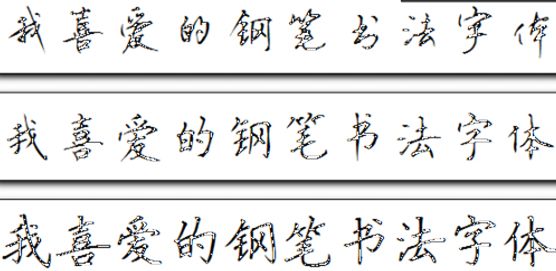
軟件介紹 軟件標簽: 字體 鋼筆字體 鋼筆硬筆書法字體有很多,小編在這里精選出三款鋼筆硬筆字體,大氣切底蘊足,自認為是目前為止較好的鋼筆書法字體:博洋楷體7000.TTF博洋行書7000.TTF方正硬筆楷書簡體.TTF 字體存放位置:c盤-windows -fonts 軟件截圖 上一張下一張(1 / 1) 安裝詳細截圖 猜你喜歡 鋼筆字體 書法字體 鋼筆字體 鋼筆字體是設計領域經常用到的字體,鋼筆字體具有鮮明的個人特征,風格多樣,深受廣告設計、平面設計師的喜愛,除了一些手寫鋼筆字體,還有正楷、行書類的鋼筆字字體,為設計師們提供了豐富的字體形式,綠色資源網也有很多鋼筆字體下載和鋼筆字體包,需要的可以看一看 查看更多>> 鋼筆書法軟件手機版 93.56M/中文/10.0/v2.1.5 安卓版下載 鋼筆之家 4.83M/中文/10.0/v1.0.2 安卓版下載 鋼筆手寫字體免費 11.71M/中文/1.2/下載 鋼筆書法入門基知識 31.79M/中文/5.0/v6.3.1 安卓版下載 浮生體 1.92M/中文/5.0/下載 伯樂鋼筆行書字體 3.53M/中文/6.6/下載 書法字體 書法字體有哪些?主要包括了硬筆書法字體、英文書法字體和毛筆書法字體三大類,綠色資源網提供了多款好看的常用各種書法字體文件打包下載,如:李旭科書法字體、啟功書法字體等,趕快下載體驗吧! 查看更多>> 蔡云漢隸書書法字體ttf 2.61M/中文/10.0/下載 黃庭堅字體 2.39M/中文/6.6/下載 李旭科書法v1.4-中 3.59M/中文/7.7/下載 金梅書法豆豆 2.03M/中文/10.0/下載 金梅新海報書法 2.24M/中文/10.0/下載 劉夢吟書法行楷字體 3.66M/中文/10.0/下載 其他版本下載 標題 大小 更新日期 下載 下載地址 電腦版 鋼筆硬筆書法字體 精選3款 點擊報錯 軟件無法下載或下載后無法使用,請點擊報錯,謝謝! 關閉報錯反饋 請描述您所遇到的錯誤,我們將盡快予以修正,謝謝! *必填項,請輸入內容 本類最新 首爾南山體字體 v1.06 官方版 潮字社風云簡ttf 潮字社凌渡鯤鵬簡體字體 潮字社曾玉波手書簡字體 微博慧心字體 阿里巴巴iconfont字體庫 相關文章 Windows 7系統默認字體還原技巧 Photoshop字體安裝使用方法和技巧 綠色資源網教你谷歌瀏覽器怎么調節字體大小 Mac下如何安裝字體?蘋果Mac系統安裝字體的三種方法 photoshop 缺少字體對照表(中英對照表)_字體中英文對照表大全 CDR字體列表缺少字體的解決方法 用戶評論 熱門評論 最新評論 發表評論 查看所有評論(0) 昵稱: 請不要評論無意義或臟話,我們所有評論會有人工審核. 字數: 0/500 (您的評論需要經過審核才能顯示)